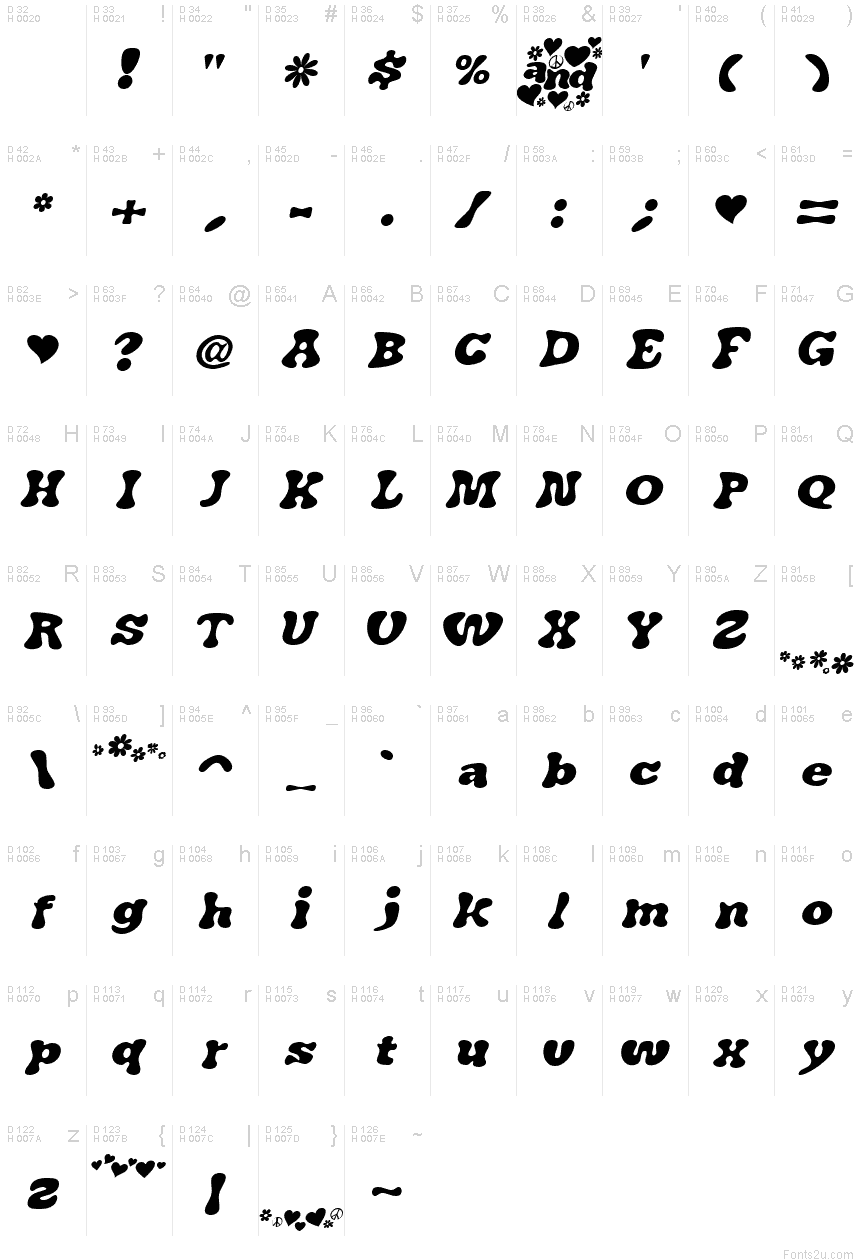
J. Airplane swash Italic
Tipografa de estilo psicodlico en homenaje a los aos 60 y principalmente a los carteles tipogrficos de conciertos de msica pop de la poca.
J. Airplane* es una fuente de estilo orgnico con Swashes.
salos en combinacin con las minsculas: [] {} <> # * &
Ejem: J. A[irplane] Swash}
Typography psychedelic style</strong> in homage to the 60s and mainly typographic posters pop music concerts of the time.
J. Airplane * is a font of organic style, with Swashes.
Use them in combination with sensitive: [] {} <> # * &